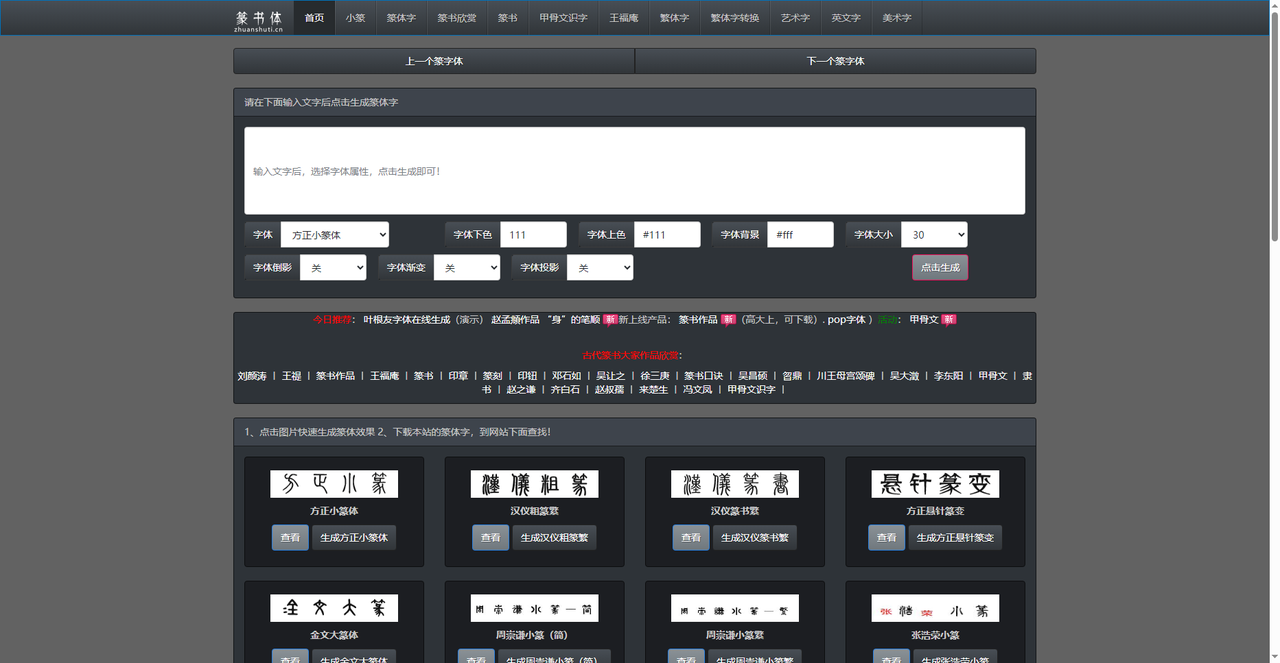
想打篆书打不出来?用这个转换器,三秒出效果
做印章设计、古风Logo、文化展板,篆书是绕不开的字体。字形修长、笔画圆转、结构匀称,自带一种庄重的金石韵味。但是,普通电脑里别说篆书了,连像样的书法体都没几个。怎么办?不用担心,现在不一样了,在线篆书转换器输入简体汉字,自动转成篆书图片,不用安装任何东西。今天实测了5款,有专业字体平台,有垂直转换站,也有学习型工具,总有一款能帮你打出想要的篆书字体。
先写字由。字由是国内最大的字体管理与应用平台,收录了多款正版篆书字体。打开字由客户端或网页版,在搜索框输入“篆书”,或通过筛选栏在字体类型中找到“篆书”分类,就能看到以下字体:
2、篆书体专业转换站
第二个网站是一个专业的篆书体在线转换平台。它的功能非常垂直,专门做各种古文字转换。首页列出了“小篆”“篆体字”“篆书欣赏”“甲骨文识字”“王福庵”“繁体字转换”等板块。核心功能在页面中央:输入文字,选择字体属性,点击“生成篆体字”。此外还有“金文转换器”“甲骨文转换器”“九叠篆转换器”等古文字工具。点击相应的按钮,就能将输入的简体文字转换成对应的篆书风格图片。页面还提供了“点击图片快速生成篆体效果”和“下载本站的篆体字”功能。对于想要临摹或下载篆书字体的用户,也有资源入口。下方还有古代篆书大家作品欣赏(刘颜涛、王福庵、邓石如等),以及甲骨文识字等学习内容。这个站既是一个工具,也是一个篆书爱好者社区。
3、字体家
第三个网站是字体家。它是一个大型中文字体平台,提供字体下载、AI造字、字体转换器等功能。在它的“字体转换器”板块下,可以找到“篆书字体在线转换”。用户选择字体(例如“汉仪亦云隶”),调整大小、背景,还可以添加抖音风格、空心字、阴影、线性渐变、径向渐变、3D效果等特效。然后输入文字,点击“在线转换”,即可生成带有特效的篆书图片。
字体家的特色在于特效丰富。如果你想要一个带金属质感或3D立体效果的篆书标题,在这里可以一步完成。此外,它还有丰富的字体标签:楷书、行书、草书、手写、瘦金体、立体字、POP字体等,方便按风格筛选。对于需要将篆书用于商业海报、电商主图的用户,字体家集转换与炫酷效果于一体,比纯图片转换更实用。
4、千千秀字
第四个网站是千千秀字。它提供“篆书、隶书、楷书、草书、行书字体在线预览”功能。页面简洁:输入文字(5-18字),选择字体(默认为“篆书”),可微调字号(+0/+2/+4),选择背景(白色/黑色/透明/卷轴),文字颜色也可自定义。点击“点此转换”,下方立即生成预览图片。
千千秀字的特点在于它并不仅仅支持篆书,而是五种主流书体一次呈现。你可以输入一句话,在同一页面分别预览篆书、隶书、楷书、草书、行书的效果,便于对比和选择。页面下方还附带了每种字体的简介,例如篆书包含大篆和小篆,隶书讲究“蚕头燕尾”,楷书端正,草书狂放,行书流畅。对于想要了解书法字体差异的用户,千千秀字既是转换工具,也是学习工具。转换结果仅供在线预览,商用需自行确认版权。
5、装饰篆书转换列表
第五个网站是一个综合字体转换平台,页面顶部有“虎年精选字体”“海报字体下载”“电商广告专用字体”“艺术字HOT”“书法字体”“花体”等分类。右侧有“手工签名设计”和“站长推荐”。在字体列表下方,有一个“开始转换”区域,可以选择“汉仪范歌笑隶书简”等字体,调节大小和背景透明,然后生成图片。虽然它的主力是隶书,但搜索或筛选也能找到篆书选项。如果你在其他站都没找到合适的转换效果,可以到这个站的分类里翻一翻,或者直接用它的“字体预览”功能快速看效果。
以上就是今天要介绍的五款篆书转换工具,其中字由最适合专业设计师,提供汉仪篆书繁、汉仪粗篆繁等正版商用篆书字体,激活后在PS里反复使用,输入你想转换的文字,选一款喜欢的篆书风格,几秒钟就能看到圆转流畅、古朴典雅的篆书效果。无论是做印章、Logo,还是学习古文字,肯定能帮你找到想要的字体。